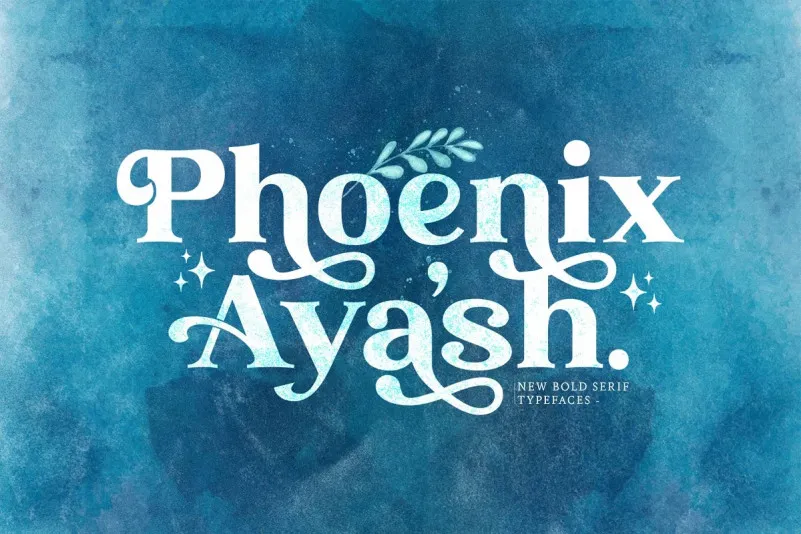
A Phoenix Ayash Font é uma elegante tipografia serif que surge com a força do modernismo, produzida pela StringLabs. Este tipo de letra séria e bold traz alternativas estilísticas e ligaturas únicas que tornam o texto ainda mais especial. As alternativas estilísticas permitem ajustes sutis para adaptar o tipo às necessidades específicas de projetos, enquanto as ligaturas facilitam a escrita fluida de caracteres complexos. Além disso, sua capacidade de se encaixar em uma ampla gama de aplicativos significa que você pode usá-la em diversas ideias criativas. Experimente juntando essa fonte à sua lista de projetos e observe como ela as torna ainda mais destacáveis. Com Phoenix Ayash Font, suas criações ganham um toque sofisticado e moderno que fazem a diferença. Esta tipografia elegante é uma excelente opção para qualquer projeto que exija um equilíbrio entre estilo formal e versatilidade prática. Seja ela usada em editoriais, materiais de marketing ou projetos digitais, Phoenix Ayash vai garantir que suas mensagens sejam percebidas como obras-primas gráficas.